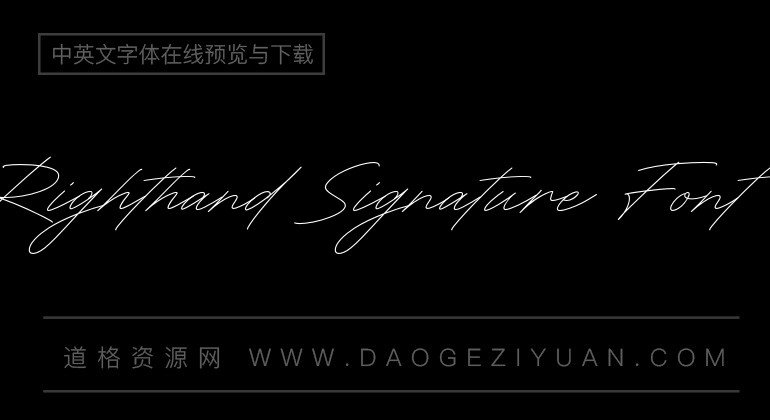
Righthand Signature Font
Righthand Signature Font是一种手写风格的签名字体,具有自然、流畅和优美的特点。这种字体的笔画仿佛是由一支签字笔书写而成,每个字母都具有独特的风格和特征。 Righthand Signature Font字体适用于各种场合,如名片、信件、海报、广告等。它可以为你的设计增添一份独特的个性和艺术感,使你的作品更加引人注目。 此外,Righthand Signature Font字体还包括多种字形和大小,方便你在不同的设计场景中使用。如果你正在寻找一种能够突出你个性和创意的签名字体,Righthand Signature Font 字体是不错的选择。
Righthand Signature Font是一款非常不错的手写艺术字体,具有很好的视觉感,适合于文化类的宣传设计、商业类品牌的广告和产品包装设计以及个性化文字排版等较多场景。